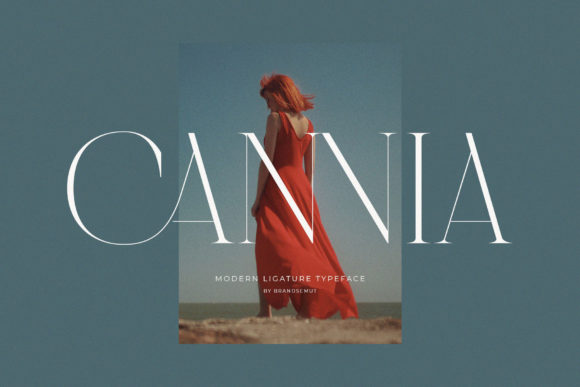
Cannia || Ligature Typeface
適切なデザイン要素を見つけるのは難しい場合がありますが、Cannia || Ligature Typefaceは作品を即座に引き立てる優れたコレクションを提供します。
POD(オンデマンド印刷)製品、結婚式の招待状、またはソーシャルメディアのグラフィックを作成している場合でも、Cannia || Ligature Typefaceは理想的です。